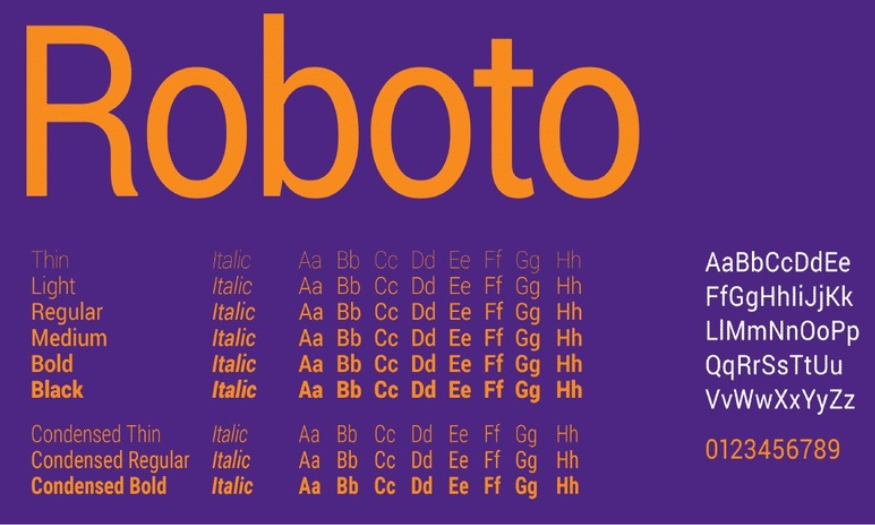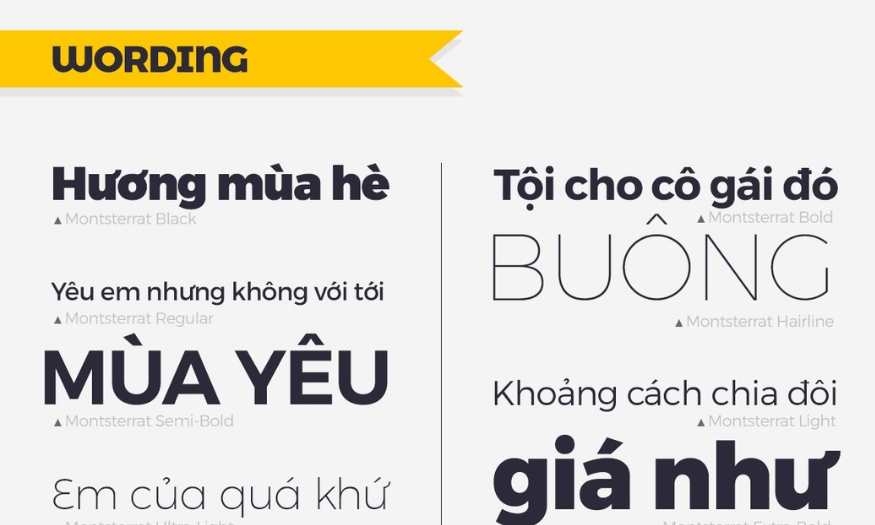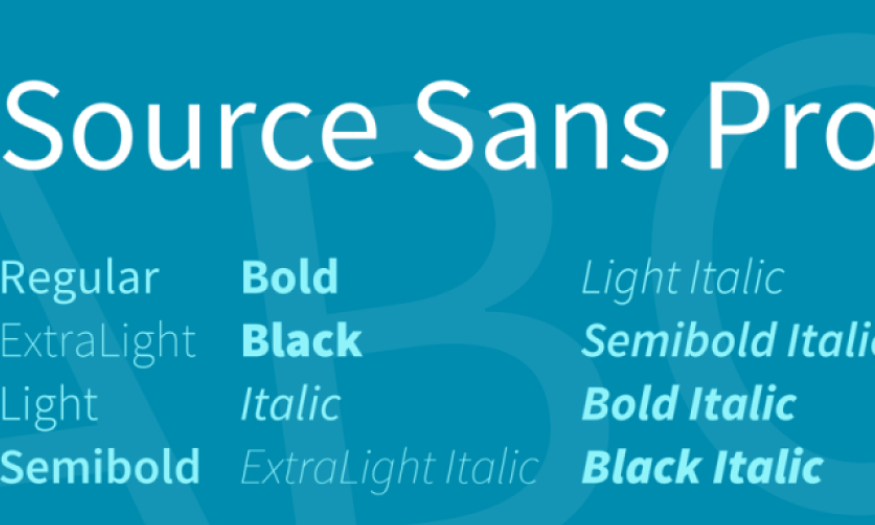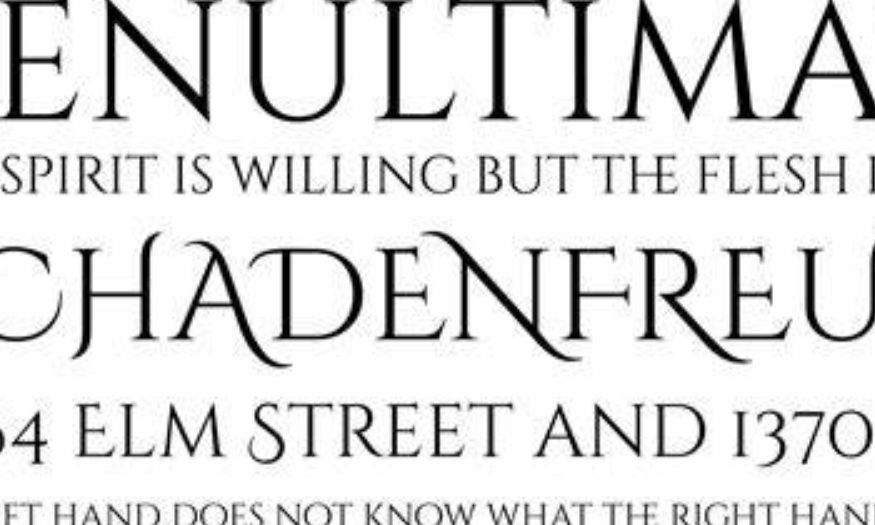
Bộ Font Miễn Phí Giúp Thiết Kế Trở Nên Chuyên Nghiệp Hơn
Trong lĩnh vực thiết kế đồ họa, font chữ không chỉ đơn thuần là công cụ truyền tải thông tin mà còn là yếu tố quyết định đến vẻ đẹp và sự chuyên nghiệp của sản phẩm. Một font chữ phù hợp không chỉ giúp nâng cao giá trị thẩm mỹ mà còn làm cho nội dung trở nên dễ đọc và cuốn hút hơn. Bài viết này sẽ giới thiệu đến bạn bộ font miễn phí, giúp bạn dễ dàng lựa chọn cho các dự án thiết kế, từ website đến brochure, từ logo đến quảng cáo. Với những font chữ này, bạn sẽ tạo ra những mẫu thiết kế ấn tượng và chuyên nghiệp mà không cần phải tốn kém chi phí. Hãy cùng Sadesign tìm hiểu ngay!
1. Roboto
Roboto là một trong những font chữ sans-serif hiện đại được yêu thích nhất hiện nay. Được thiết kế bởi Google, Roboto không chỉ mang đến sự dễ đọc mà còn tạo cảm giác thân thiện, gần gũi. Font chữ này rất phù hợp cho cả tiêu đề lẫn nội dung chính, giúp người dùng dễ dàng tiếp cận thông tin một cách nhanh chóng và hiệu quả.
Một trong những điểm nổi bật của Roboto là khả năng thích ứng với nhiều loại thiết kế khác nhau. Bất kể bạn đang làm việc trên một trang web, một ứng dụng di động hay tài liệu in ấn, Roboto đều có thể đáp ứng tốt nhu cầu của bạn. Với nhiều độ dày khác nhau, bạn có thể linh hoạt lựa chọn kiểu chữ phù hợp với từng phần của thiết kế.
Ngoài ra, thiết kế của Roboto còn thể hiện sự hiện đại và tinh tế, giúp sản phẩm của bạn trở nên chuyên nghiệp hơn. Việc sử dụng Roboto không chỉ giúp tăng tính thẩm mỹ mà còn tạo ra sự đồng nhất trong toàn bộ thiết kế, từ màu sắc đến hình ảnh. Đặc biệt, với sự hỗ trợ của Google Fonts, việc tích hợp Roboto vào các dự án trở nên dễ dàng và nhanh chóng hơn bao giờ hết.
2. Open Sans
Open Sans là một trong những font chữ phổ biến nhất trên thế giới và được sử dụng rộng rãi trong thiết kế web. Được thiết kế bởi Steve Matteson, Open Sans mang đến sự thanh thoát và dễ đọc, làm cho nó trở thành lựa chọn lý tưởng cho các trang web và tài liệu in ấn. Font chữ này có nhiều kiểu chữ khác nhau, giúp bạn linh hoạt trong việc lựa chọn cho từng ngữ cảnh cụ thể.
Một trong những điểm mạnh của Open Sans là khả năng hiển thị tốt trên nhiều thiết bị khác nhau, từ máy tính để bàn đến điện thoại di động. Điều này rất quan trọng trong thời đại công nghệ hiện nay, khi mà người dùng có thể truy cập thông tin từ bất kỳ đâu. Sự rõ ràng và dễ đọc của Open Sans giúp người dùng không bị phân tâm, từ đó tập trung vào nội dung chính.
Ngoài ra, Open Sans cũng rất phổ biến trong cộng đồng thiết kế nhờ vào vẻ đẹp hiện đại và dễ tiếp cận. Nó thường được sử dụng cho các trang web thương mại điện tử, blog cá nhân, và thậm chí là các tài liệu marketing. Nhờ vào sự linh hoạt và tính thẩm mỹ cao, Open Sans đã trở thành một phần không thể thiếu trong bộ công cụ thiết kế của nhiều nhà thiết kế.
3. Lato
Lato là một font chữ sans-serif với các đường nét mềm mại và hiện đại. Được thiết kế bởi Łukasz Dziedzic, Lato mang đến sự sang trọng và thanh lịch, làm cho nó trở thành lựa chọn lý tưởng cho nhiều loại dự án khác nhau. Với sự kết hợp hoàn hảo giữa tính năng và thẩm mỹ, Lato có thể được sử dụng từ quảng cáo đến thiết kế giao diện.
Lato có nhiều kiểu dáng khác nhau, từ mảnh mai đến đậm, cho phép bạn dễ dàng chọn lựa theo ý muốn. Điều này giúp bạn tạo nên sự phong phú trong thiết kế mà vẫn giữ được sự đồng nhất. Font chữ này đặc biệt thích hợp cho các tiêu đề, nhấn mạnh và nội dung chính, giúp người đọc dễ dàng nắm bắt thông tin.
Một điểm cộng lớn của Lato là khả năng hoạt động tốt trong các thiết kế trực tuyến. Với kích thước chữ nhỏ, Lato vẫn giữ được độ rõ ràng và sắc nét, giúp người dùng không bị căng mắt khi đọc. Điều này khiến Lato trở thành lựa chọn hàng đầu cho các trang web cần sự chuyên nghiệp và dễ tiếp cận.
4. Montserrat
Montserrat nổi bật với phong cách hiện đại và đô thị, mang đến cảm giác mạnh mẽ và cá tính. Được thiết kế bởi Julieta Ulanovsky, Montserrat lấy cảm hứng từ các biển hiệu và phong cách kiến trúc của Buenos Aires. Font chữ này rất thích hợp cho các tiêu đề lớn và thu hút sự chú ý, làm cho nó trở thành lựa chọn hoàn hảo cho các dự án quảng cáo và truyền thông.
Với các đường nét dày và hình dáng độc đáo, Montserrat vừa thể hiện sự mạnh mẽ vừa mang lại cảm giác thân thiện. Điều này giúp bạn tạo ra những thiết kế nổi bật và đầy ấn tượng. Montserrat cũng rất linh hoạt, có thể được sử dụng cho cả nội dung chính và tiêu đề, giúp bạn dễ dàng tạo ra sự đồng nhất trong thiết kế.
Bên cạnh đó, Montserrat cũng hỗ trợ tốt cho nhiều ngôn ngữ, giúp bạn mở rộng đối tượng người dùng. Với sự phổ biến ngày càng tăng, Montserrat đã trở thành một trong những font chữ yêu thích trong cộng đồng thiết kế, nhờ vào vẻ đẹp độc đáo và tính linh hoạt của nó.
13. Kết Luận
Việc lựa chọn font chữ phù hợp là một bước quan trọng trong quy trình thiết kế, ảnh hưởng trực tiếp đến cách mà người xem tiếp nhận thông tin. Bộ 10 font miễn phí mà chúng tôi giới thiệu không chỉ mang đến tính thẩm mỹ cao mà còn đảm bảo sự dễ đọc và khả năng tương thích với nhiều loại dự án khác nhau. Từ sự hiện đại, trẻ trung của Poppins đến sự sang trọng, thanh lịch của Playfair Display, mỗi font chữ đều có nét đẹp và tính năng riêng, giúp bạn dễ dàng thể hiện phong cách cá nhân trong thiết kế.